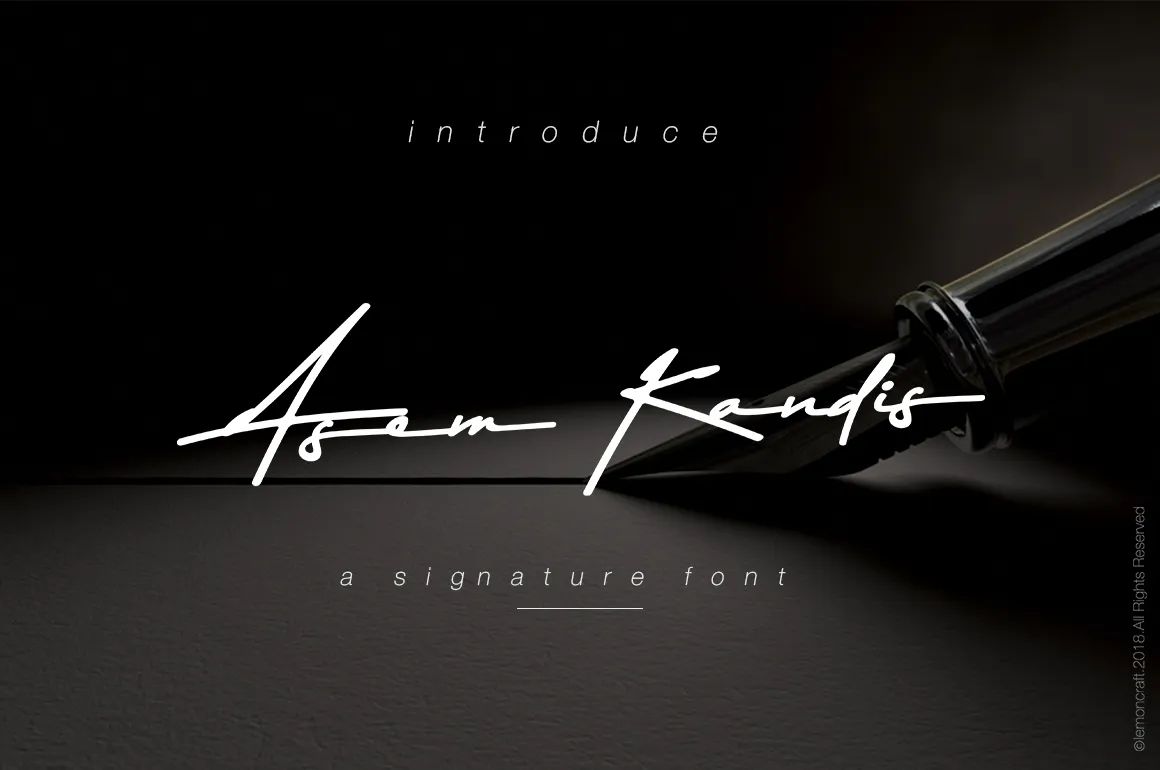
Asem Kandis Signature Font – Fonte Grátis
Asem Kandis Signature Font
A Asem Kandis Font é uma elegante assinatura script que se destaca tanto por sua modernidade quanto pela sofisticação profissional. Desenvolvida e compartilhada pelo designer zziplex, esta fonte tem tudo o que você precisa para dar um toque único em seus projetos. Com um design meticulosamente cuidado, ela oferece uma completa coleção de letras minúsculas e maiúsculas, marcadores de pontuação e números, além de um conjunto sofisticado de ligações. Sujeito a qualquer projeto que esteja buscando dar um toque elegante, a Asem Kandis Font é perfeita para assinaturas, convites de casamento, logotipos elegantes e até mesmo arte em cerâmica. Seja qual for o seu uso, ela trará uma vibração prestigiosa a qualquer trabalho.